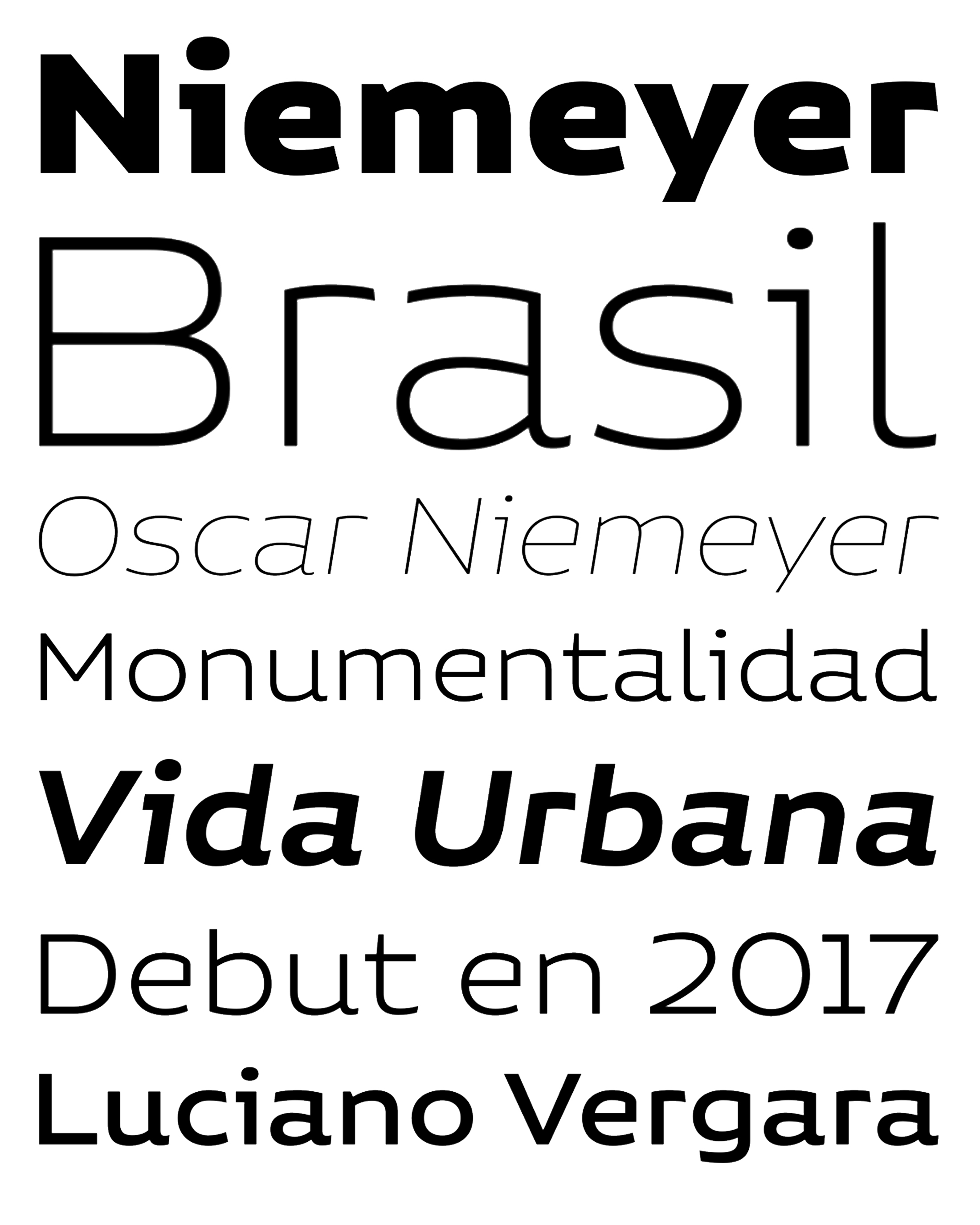
| Año | 2017 |
| Créditos | Luciano Vergara |
| Descripción | Oscar Niemeyer es uno de los más grandes arquitectos de nuestro tiempo. Su manera única de mezclar líneas rectas y curvas abstractas da lugar a un estilo inconfundible y característico. Este tipo de letra es mi propio homenaje al arquitecto brasileño Oscar Niemeyer. El proceso de diseño comenzó cuando mi mujer y yo visitamos Brasil mientras ella impartía una serie de talleres de caligrafía. En mi tiempo libre, paseaba por las calles de hermosas ciudades como Río de Janeiro o São Paulo, disfrutando de la arquitectura local y la vida urbana. También tuve la oportunidad de asistir a algunos de los talleres, durante los cuales pude observar la orgánica de la caligrafía y de la gente. Entonces, empecé a dibujar algunas formas que reflejaban todo lo relacionado con este hermoso lugar: La arquitectura y la obra de Niemeyer y, según sus propias palabras, "las curvas del cuerpo de la mujer amada". Este versátil tipo de letra está disponible en 8 pesos con cursivas a juego, caracteres alternativos, figuras de estilo antiguo y mucho más. Niemeyer es ideal para logotipos, publicidad, publicaciones, marcas y uso corporativo. Un agradecimiento especial a todo el equipo de Latinotype (especialmente a César Araya) por su apoyo, su ayuda con las correcciones y la edición digital. |
| Familia(s) | Thin, Thin It, Ultra Light It, Light, Light It, Regular, Regular It, Medium, Medium It, Semi Bold, Semi Bold It, Bold, Bold It, Black, Black It |
| Estilos | 16 |